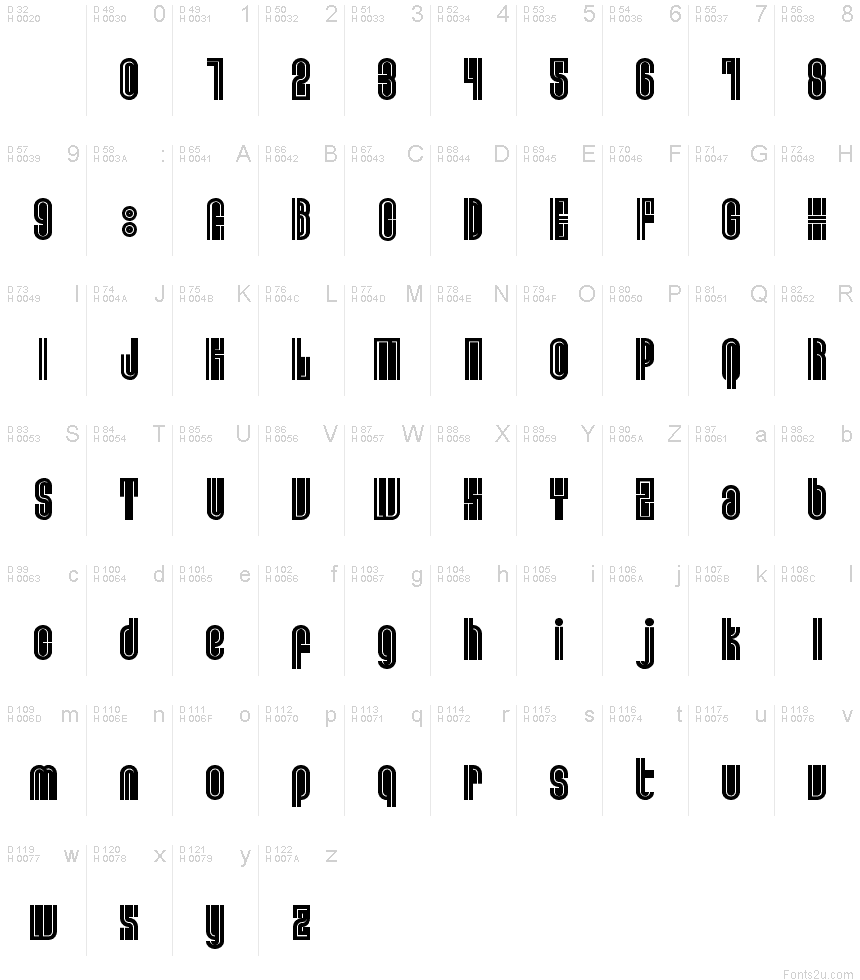
KFine to darmowy, geometryczny krój pisma typu display o ultra-skondensowanej, konturowej budowie. Jego wysokie wielkie litery sprowadzają znaki do linii prostych, kątów prostych i ciasnych łuków, przywodząc na myśl zarówno liternictwo Art déco, jak i schematy układów elektrycznych.
Fani muzyki elektronicznej i retrofuturyzmu stanowią dla niego idealne dopasowanie. Na okładkach płyt, plakatach klubowych i grafikach gier formy przypominające labirynt mogą również kształtować wizerunek salonów gier lub wydarzeń technologicznych, zmieniając liternictwo w liniowy emblemat.